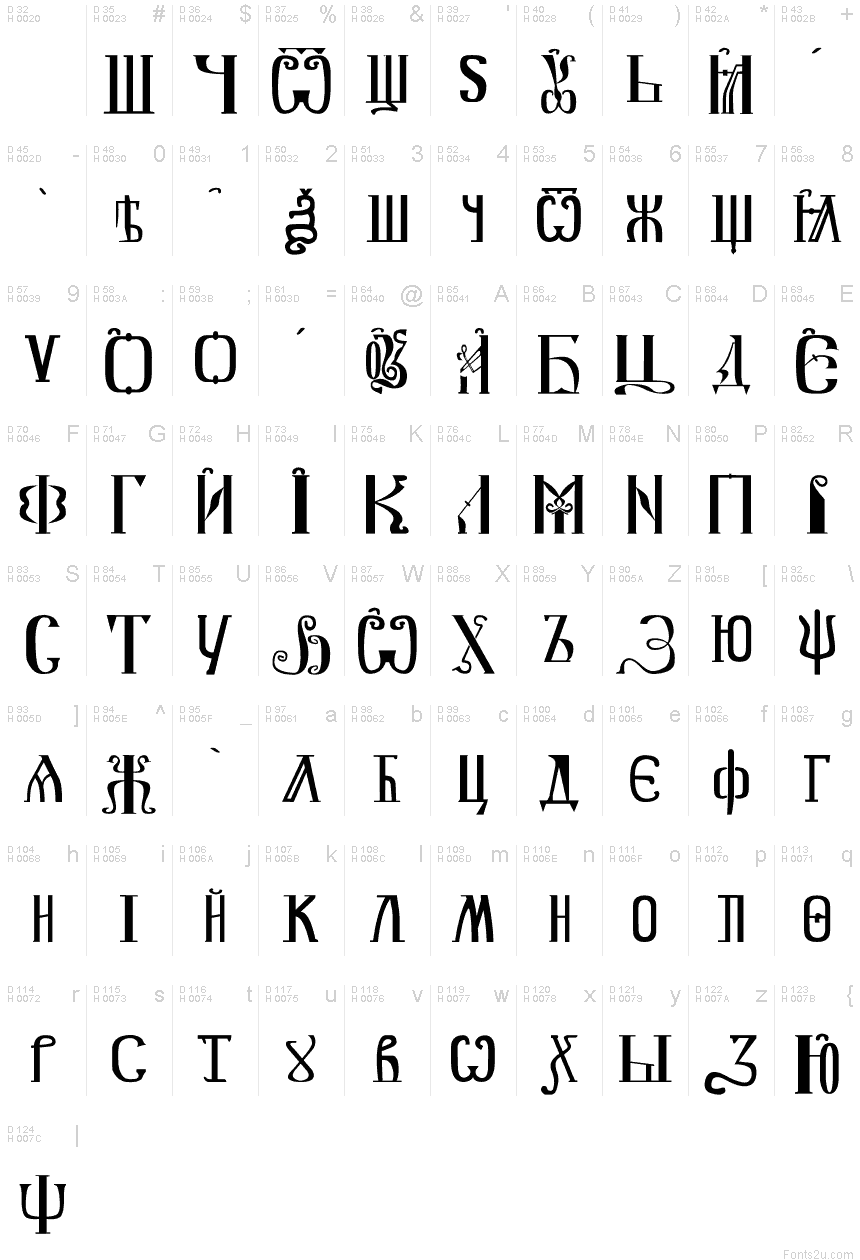
Juhasevic P è un font serif gratuito per titoli, caratterizzato da un tono maestoso ispirato all'epoca dei poster. Le lettere mescolano proporzioni alte e strette con un contrasto elevato, curve svasate e giunzioni appuntite che conferiscono al carattere un ritmo quasi teatrale, mentre alcuni glifi presentano incroci interni insoliti e forme aperte dal gusto squisitamente ornamentale.
Si presta perfettamente a testate, manifesti culturali, copertine di libri, titoli e monogrammi, dove queste maiuscole drammatiche riescono a sostenere una riga da sole. Come font gratuito, JuhasevicP risulta particolarmente efficace in contesti brevi, ideale se cerchi un tocco letterario o storico senza rinunciare a un taglio grafico netto.
JuhasevicP